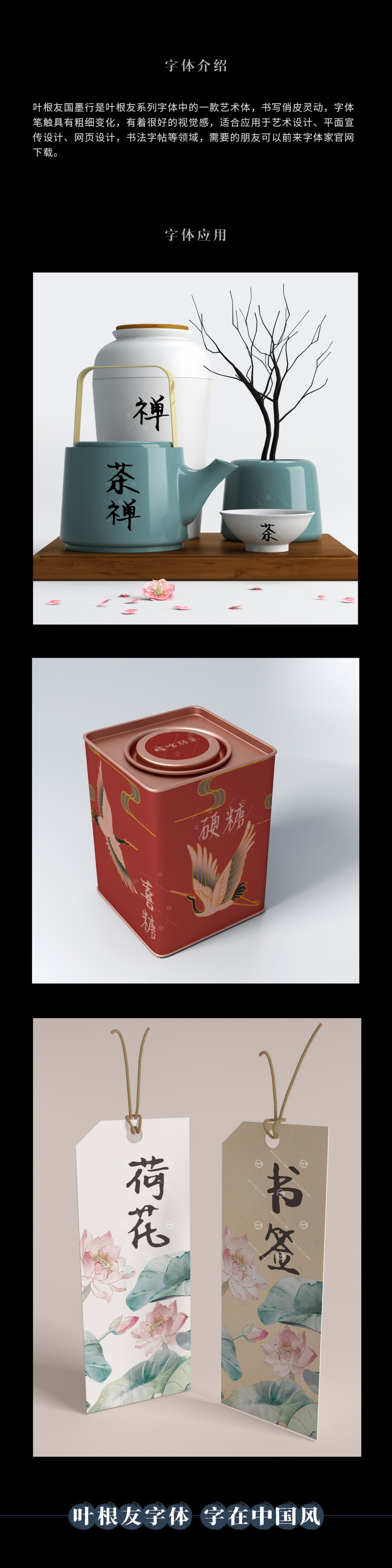
葉根友國(guó)墨行
葉根友國(guó)墨行是葉根友系列字體中的一款藝術(shù)體,書(shū)寫(xiě)俏皮靈動(dòng),字體筆觸具有粗細(xì)變化,有著很好的視覺(jué)感,適合應(yīng)用于藝術(shù)設(shè)計(jì)、平面宣傳設(shè)計(jì)、網(wǎng)頁(yè)設(shè)計(jì),書(shū)法字帖等領(lǐng)域,需要的朋友可以前來(lái)字體家官網(wǎng)下載。